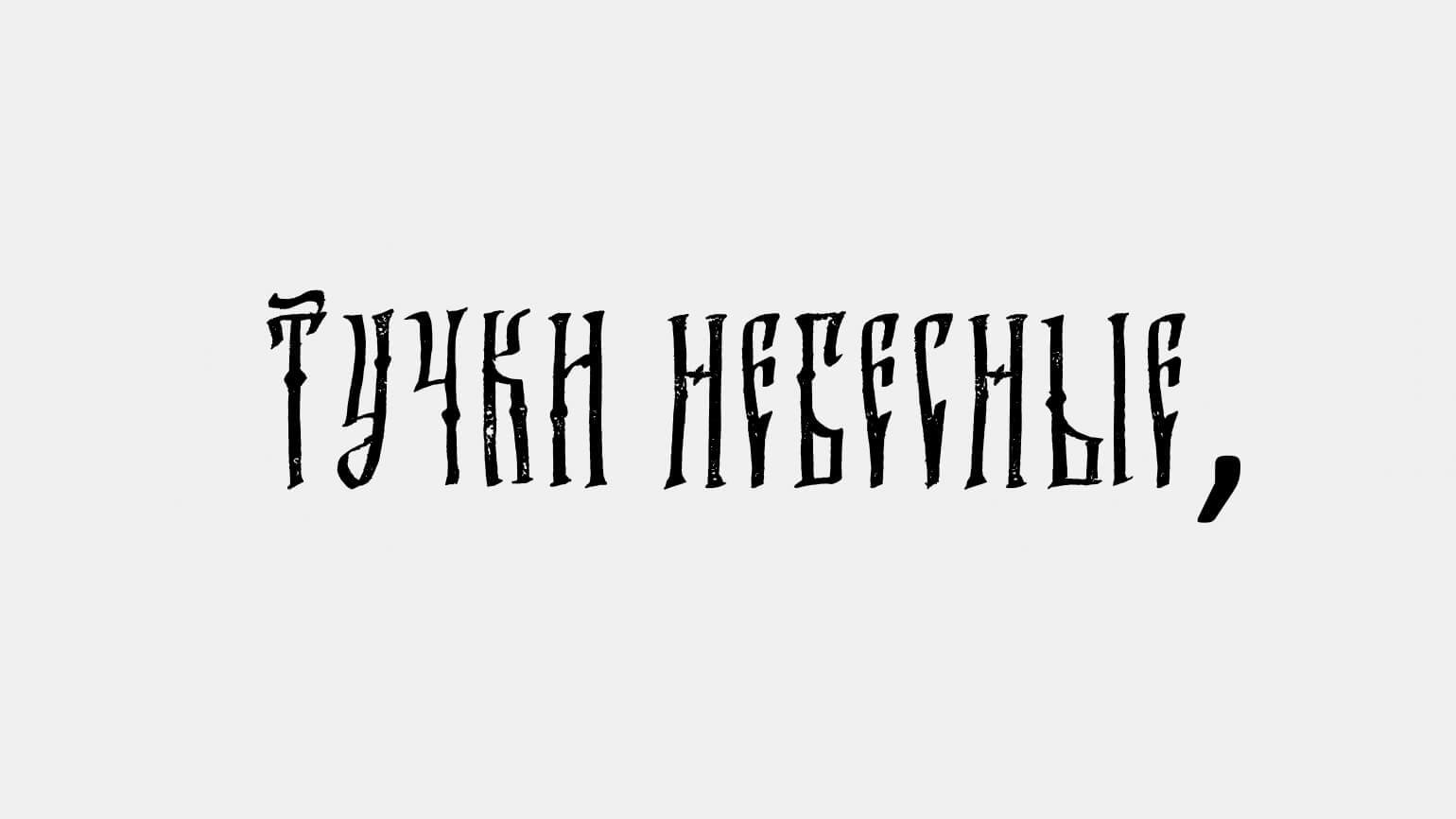
Кириллица: 24 шрифта для дизайн-проектов
Платные и бесплатные, декоративные и рабочие лошадки. Для сайтов, айдентики и больших текстов.
Даём подборку новых шрифтов с кириллицей:
Шрифты для заголовков и яркого брендинга
Reznovich
Стиль: акцидентный шрифт на основе русской вязи, вырезанный вручную в деревянных формах.
Состав: только кириллица. В нём нет цифр, латиницы и специальных знаков.
Для чего подходит: этим шрифтом можно оформлять упаковку традиционных натуральных продуктов, тексты в печатной продукции на исторические темы — например, открыток. Или смело экспериментировать и создавать неожиданные решения.
Belarus
Стиль: декоративная узкая ленточная антиква. Вдохновением для её рисунка послужили работы советского конструктивиста Соломона Телингатера.
Состав: кириллица, латиница, цифры и основные знаки пунктуации, типографские символы.
Для чего подходит: для вывесок, постеров, заголовков и небольших выносных фрагментов текста.
Cakra
Стиль: игривый и адаптивный акцидентный гротеск ― благодаря лигатурам, которые выглядят, будто они были случайно сгенерированы. Изначально Cakra был создан для айдентики видеостудии на факультете искусств в Университете Брно, но авторы решили бесплатно поделиться им с миром.
Состав: в шрифте одно начертание и только прописные буквы, но есть четыре набора стилистических сетов, и всего в нём 2000 глифов, в том числе собственные эмодзи. В Cakra есть латиница и кириллица, а поддерживает он более 130 языков.
Для чего подходит: для брендинга современных продуктов, одежды, детских товаров, или яркой типографики на постерах о мероприятиях, или сайтов-портфолио дизайнеров.
Ganesha
Стиль: акцидентный шрифт, рисунок которого основан на алфавитах Индостана — тамильском, деванагари, телугу, санскрите и бенгальском.
Состав: только прописные латиница и кириллица, три стилистических сета, цифры 0–9, основные знаки препинания, некоторые математические знаки и валютные знаки рубля, доллара и рупий. И ещё интересно, что знак * сделан как традиционный восточный рисунок звезды.
Для чего подходит: для айдентики этнических продуктов, брендинга йога-студий и магазинов экзотики. Если в теме проекта есть привязка к Индии, Бангладеш, Тайваню и прочим странам Юго-Восточной Азии, он будет отличной акциденцией для заголовков и названий.
New Mexika
Стиль: акцидентный гротеск с крупными декоративными ловушками для чернил, или inktraps.
Состав: прописные и строчные буквы латиницы и кириллицы, основные знаки препинания и цифры.
Для чего подходит: для крупных заголовков и названий на баннерах и билбордах, навигации в фирменном стиле и минималистичной упаковки.
Curvede Pro
Стиль: утончённый и элегантный шрифт с декоративными засечками и сказочным характером.
Состав: кириллица и латиница в одном начертании Regular, цифры, знаки пунктуации и основные символы, а также набор лигатур.
Для чего подходит: для логотипов, заголовков в журналах и на сайтах или для брендинга ресторанов современной кухни.
Become
Скриншот: сайт MyFonts / Skillbox Media
Стиль: дисплейный шрифт с игривым характером. В нём «обычные» буквы легко читаемого гротеска сочетаются с буквами, похожими на иллюстрации.
Состав: латиница и кириллица в 18 начертаниях — от очень тонкого до супержирного Black, включая курсивы. Плюс — стилистические сеты и лигатуры fi, fl.
Для чего подходит: шрифт довольно универсальный — его можно использовать в типографике для любых веб-магазинов и приложений или в печати. Удобно то, что читабельность и визуальная лёгкость Become позволяет применять его в дизайне мелкой продукции — например, визиток или этикеток.
Old Union
Стиль: дизайн этого выразительного шрифта отсылает к графике раннесоветского времени, но вместе с тем он выглядит современно и «чисто», а не просто перерисованной копией.
Состав: в гарнитуре есть два шрифта — основной в начертании Regular и наклонный. Авторы разработали прописные и строчные буквы латиницы и кириллицы, цифры и самые распространённые символы.
Для чего подходит: для оформления музыкальных продуктов, печатных и веб‑журналов.